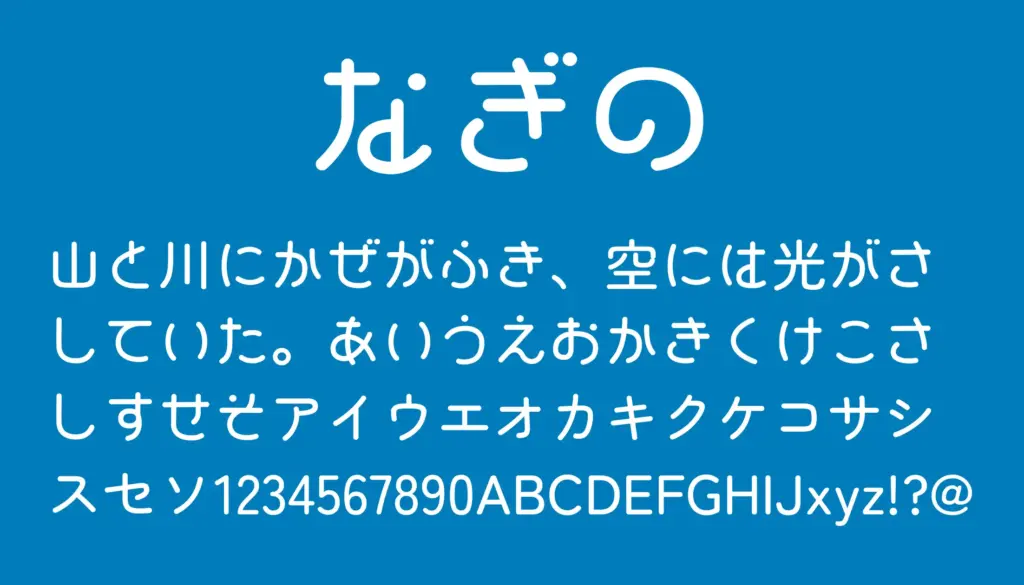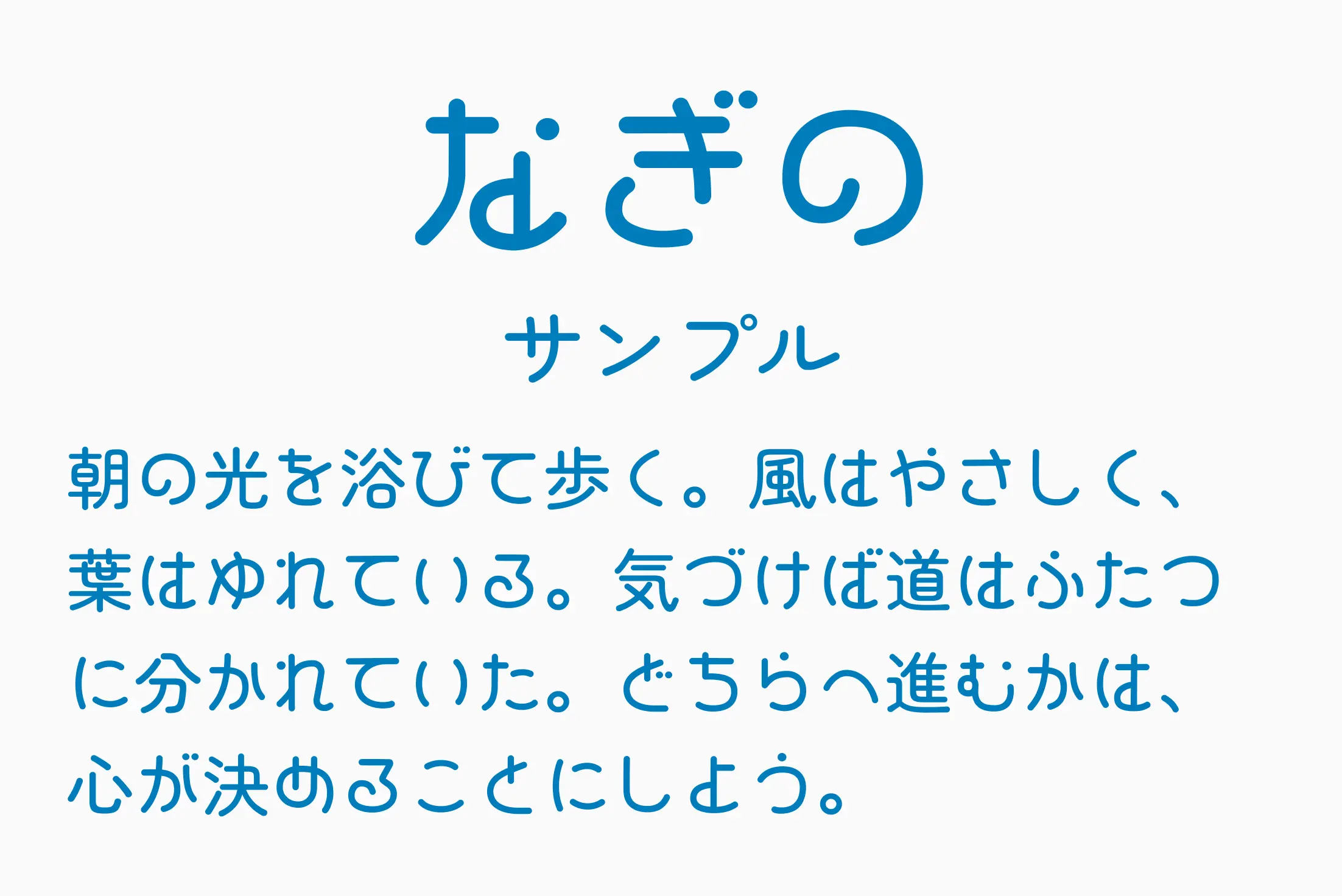
やわらかな海の泡やレトロな看板文字を思わせる、丸みのある手描き風ゴシック体です。明治〜昭和の雰囲気を感じる親しみやすいデザインで、特に「な」「ま」「よ」などの字形には横書きに映える“くるん”とした結びが施されています。素朴で温かみのある線と、クセになりすぎない可愛らしさが魅力で、子供向けコンテンツやポップなチラシ、レトロ風ロゴなど幅広い場面で活躍します。
なぎの